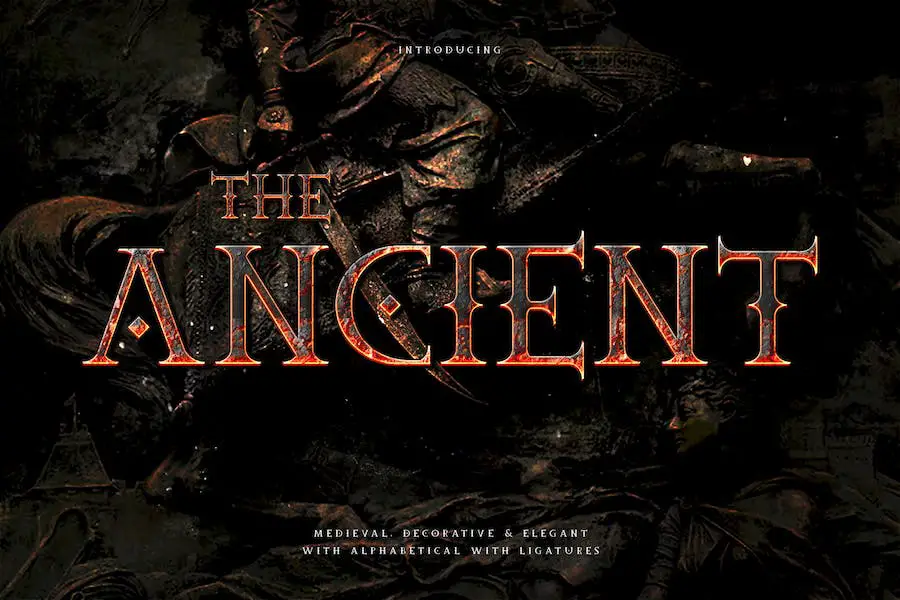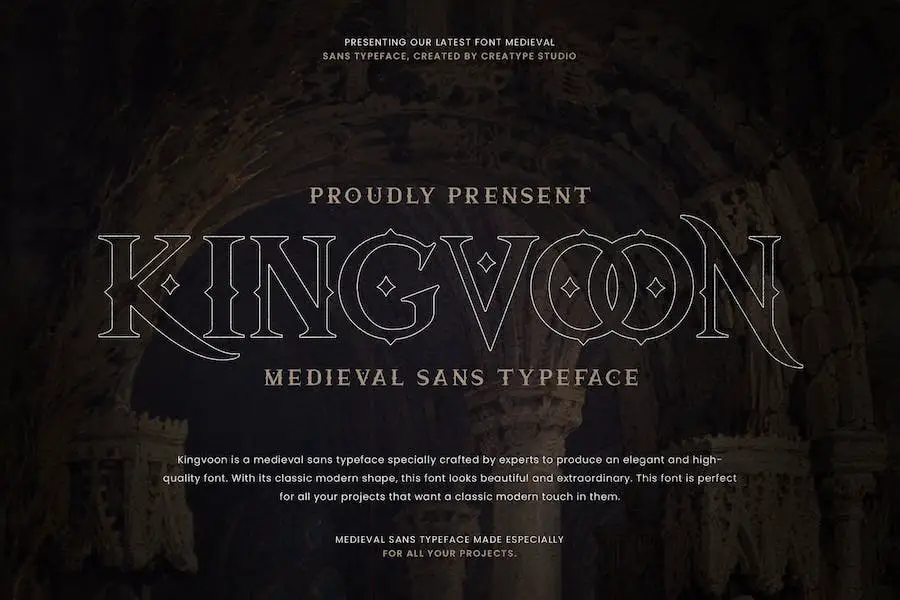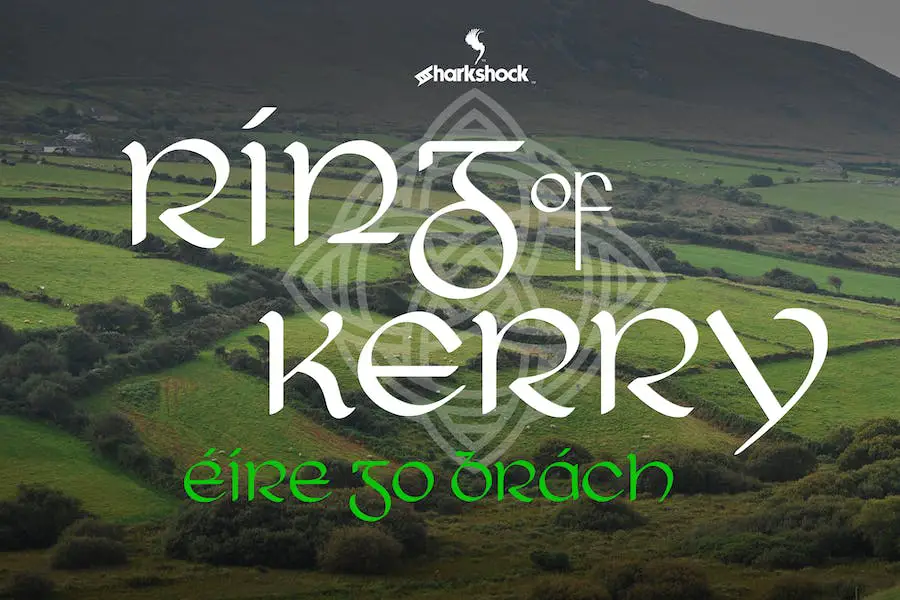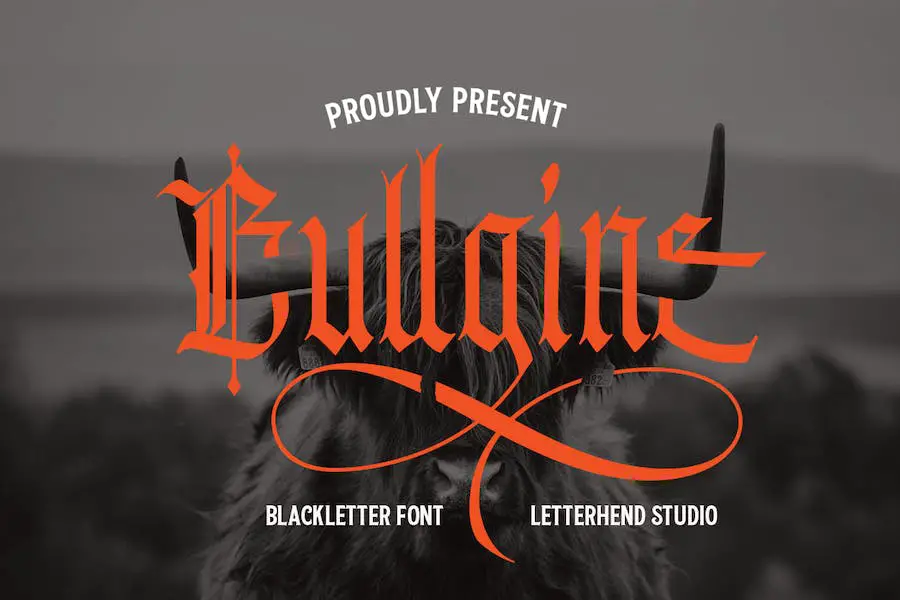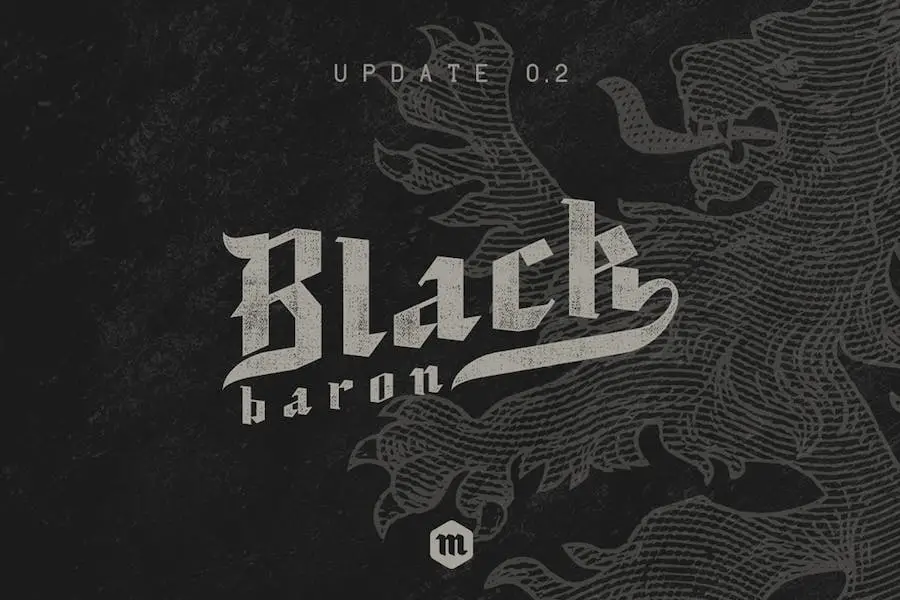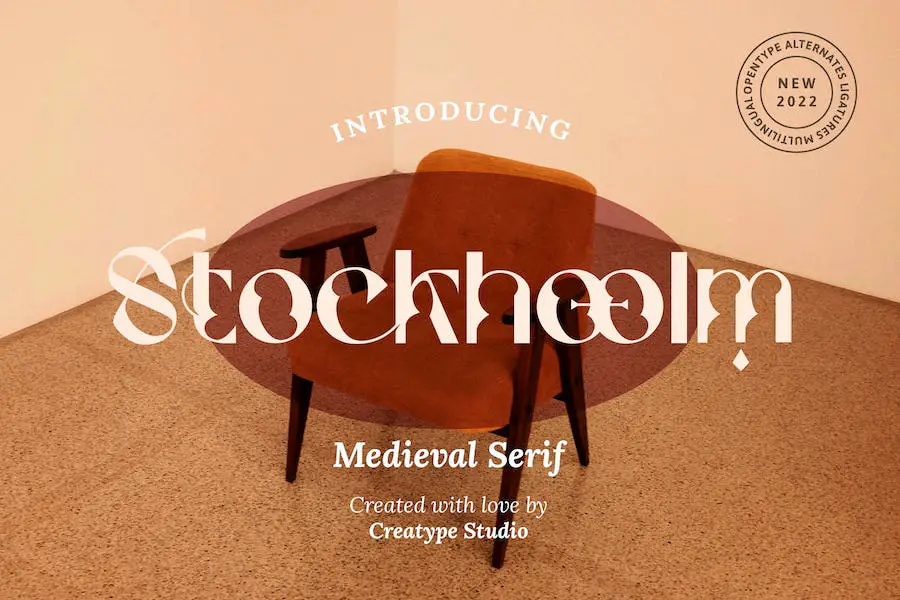
28 melhores fontes medievais de 2023 (grátis e premium)
Publicados: 2023-09-22Você é um designer gráfico em busca da fonte perfeita para valorizar seus projetos? Não procure mais!
Nesta postagem do blog, exploraremos as 28 melhores fontes medievais para 2023, tanto gratuitas quanto premium. Se você está pronto para adicionar um toque de charme e elegância do velho mundo aos seus designs, continue lendo!
Agora, você deve estar se perguntando: por que fontes medievais? Bem, essas fontes são perfeitas para criar uma sensação de antiguidade e capturar a essência de tempos passados.
Esteja você trabalhando em um projeto histórico, um design com tema de fantasia ou simplesmente queira infundir um toque de nostalgia em seu trabalho artístico, as fontes medievais podem realmente elevar seu trabalho ao próximo nível.
Neste artigo, mergulharemos nas 28 principais fontes medievais de 2023. Forneceremos as melhores opções, que vão desde recursos gratuitos até fontes premium que oferecem ainda mais versatilidade e personalização.
Entendemos que, como designer gráfico, você está procurando fontes que não apenas tenham uma ótima aparência, mas também forneçam funcionalidade e facilidade de uso. É por isso que selecionamos cuidadosamente esta lista para trazer a você as fontes medievais mais excepcionais disponíveis.
Então, se você está pronto para embarcar em uma viagem no tempo e criar designs cativantes inspirados na era medieval, vamos mergulhar e explorar juntos o vasto mundo das fontes medievais.
Prepare-se para transportar seu público para uma época passada repleta de cavaleiros, castelos e o charme atemporal da Idade Média.
Melhores fontes medievais premium
Quer adicionar um toque autêntico da Idade Média aos seus projetos de design? Não procure mais, nossa seleção com curadoria das melhores fontes medievais premium. Descubra a fonte perfeita para trazer um toque de história e elegância aos seus designs.
Fúrcula
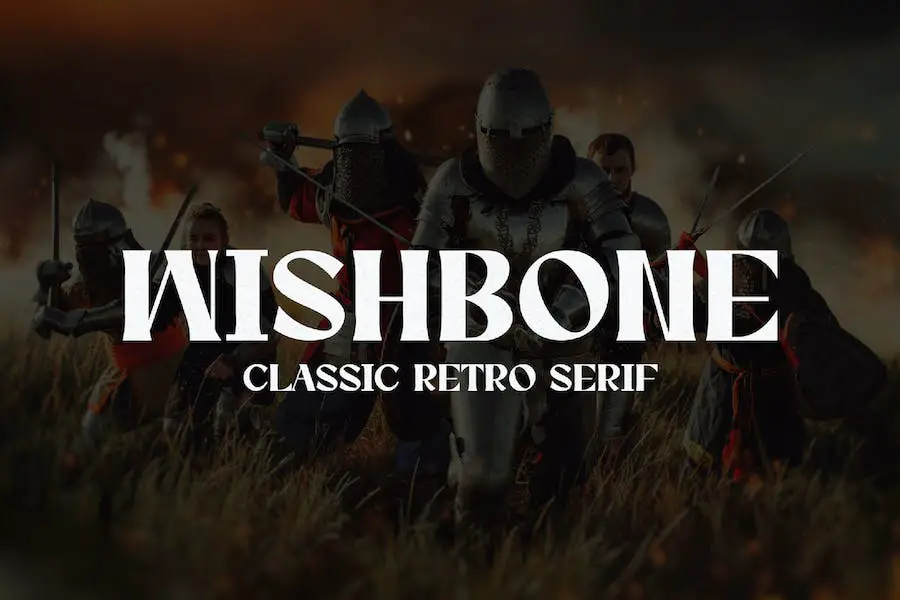
Wishbone é uma fonte serifada clássica que se inspira na tipografia medieval. Suas letras têm um toque cru e ousado, sendo a escolha perfeita para projetos que exigem um visual ousado e complexo.
Essa fonte é incrivelmente versátil e pode trazer um toque de autenticidade a vários empreendimentos de design, incluindo branding, projetos históricos, capas de livros, revistas, pôsteres, casamentos, postagens em mídias sociais, sites, publicidade, citações e eventos especiais.
Sua simplicidade e legibilidade o tornam adequado tanto para cabeçalho quanto para corpo de texto, garantindo que seu conteúdo se destaque e ao mesmo tempo seja fácil de digerir.
Lua de Prata
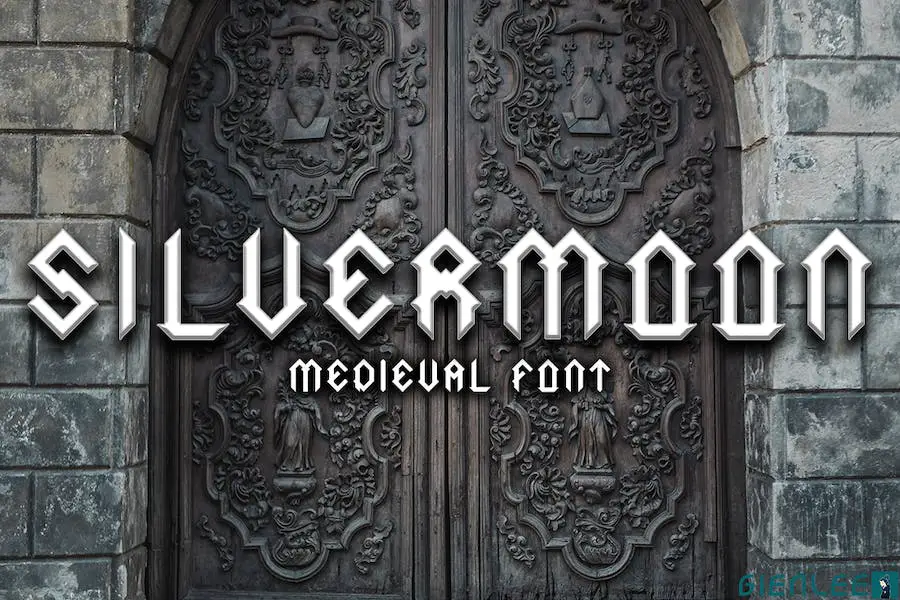
Silvermoon é uma fonte gótica medieval que captura a essência da Idade Média, com um toque adicional de elegância dos elementos de cristal e pedra prateada.
Seu estilo único é perfeito para designers gráficos que buscam aprimorar seus projetos com um design de inspiração medieval. Com Silvermoon, você pode trazer um ar de mística e charme histórico às suas criações.
Esta fonte medieval foi projetada especificamente para transportar os espectadores ao mundo encantador de cavaleiros, castelos e aventuras épicas. Seus detalhes intrincados e floreios ornamentados acrescentam profundidade e autenticidade a qualquer texto.
Mosteiro
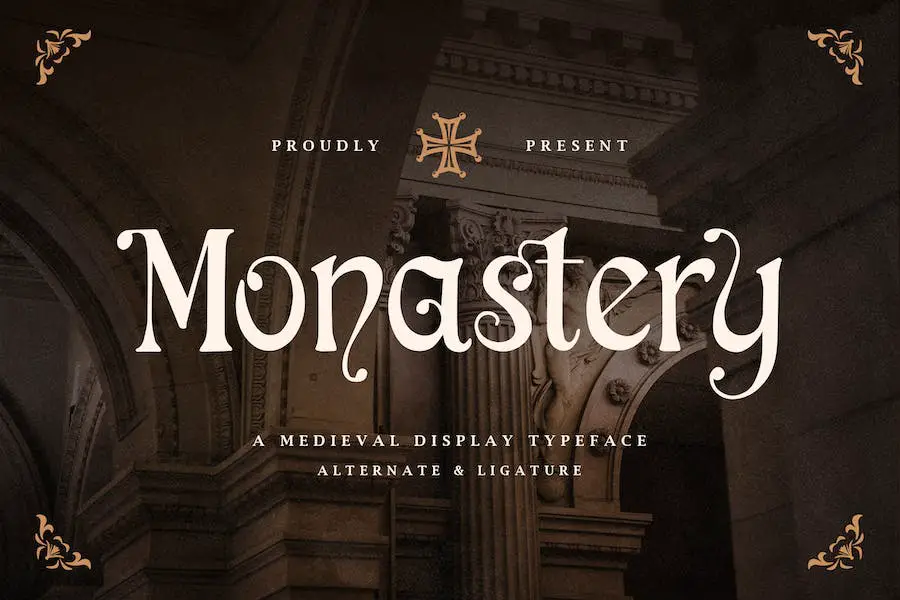
Monastery é uma fonte de exibição divertida e interessante que exala uma vibração medieval única. Inspirando-se nos tipos de letras de aparência gótica da era medieval, esta fonte é perfeita para adicionar um toque histórico aos seus projetos.
Esteja você trabalhando em um design com tema medieval ou simplesmente queira incorporar algum charme do velho mundo, Monastery é a fonte para você. Seu estilo distinto irá cativar o seu público e transportá-lo para uma época passada.
Então, se você está procurando uma fonte gótica medieval ou uma fonte para escrita medieval, não procure mais, Monastery. É garantido que irá melhorar o design dos seus projetos e dar-lhes vida.
Goldiwak
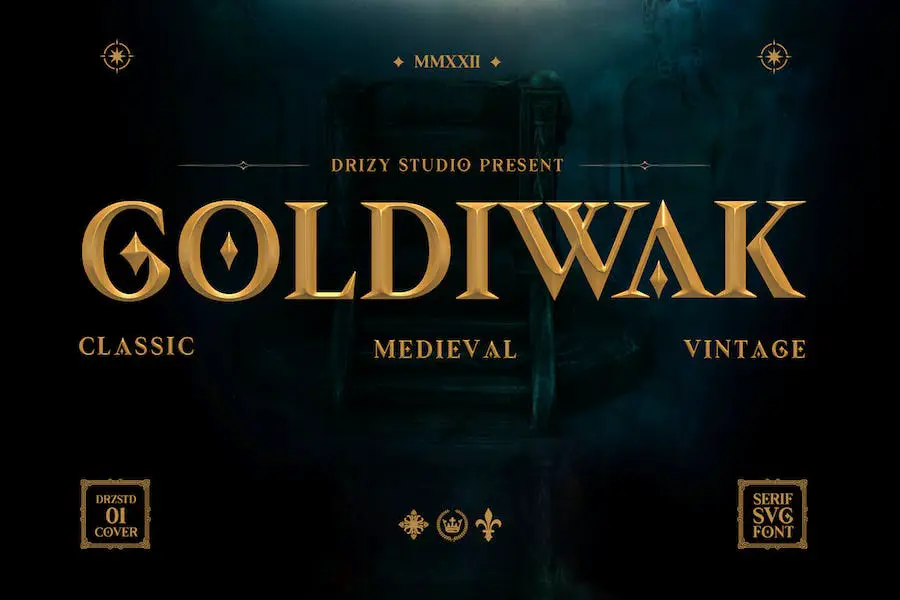
Goldiwak é uma fonte medieval requintada criada pelo Drizy Studio. Esta fonte é absolutamente obrigatória para designers gráficos que desejam aprimorar o design de seus projetos com um toque de charme medieval clássico. Com seus estilos versáteis, Goldiwak é a escolha perfeita para qualquer projeto que requeira uma temática medieval ou clássica.
Uma das características de destaque do Goldiwak são suas alternativas e ligaduras. Esses caracteres únicos adicionam uma camada extra de elegância e sofisticação aos seus designs, permitindo que você crie uma tipografia impressionante que se destaca da multidão.
Esteja você trabalhando em um Google Doc, projeto da Adobe ou usando ferramentas de design populares como Canva, Circuit ou Figma, Goldiwak é compatível e se integra perfeitamente a essas plataformas. Sua natureza amigável garante uma experiência tranquila e descomplicada, mesmo para iniciantes.
Astaroth
Lembre-se de que escolher a fonte medieval perfeita pode fazer uma grande diferença em seus projetos de design. Então vá em frente, explore a vasta gama de opções e deixe sua criatividade florescer com essas incríveis fontes medievais.